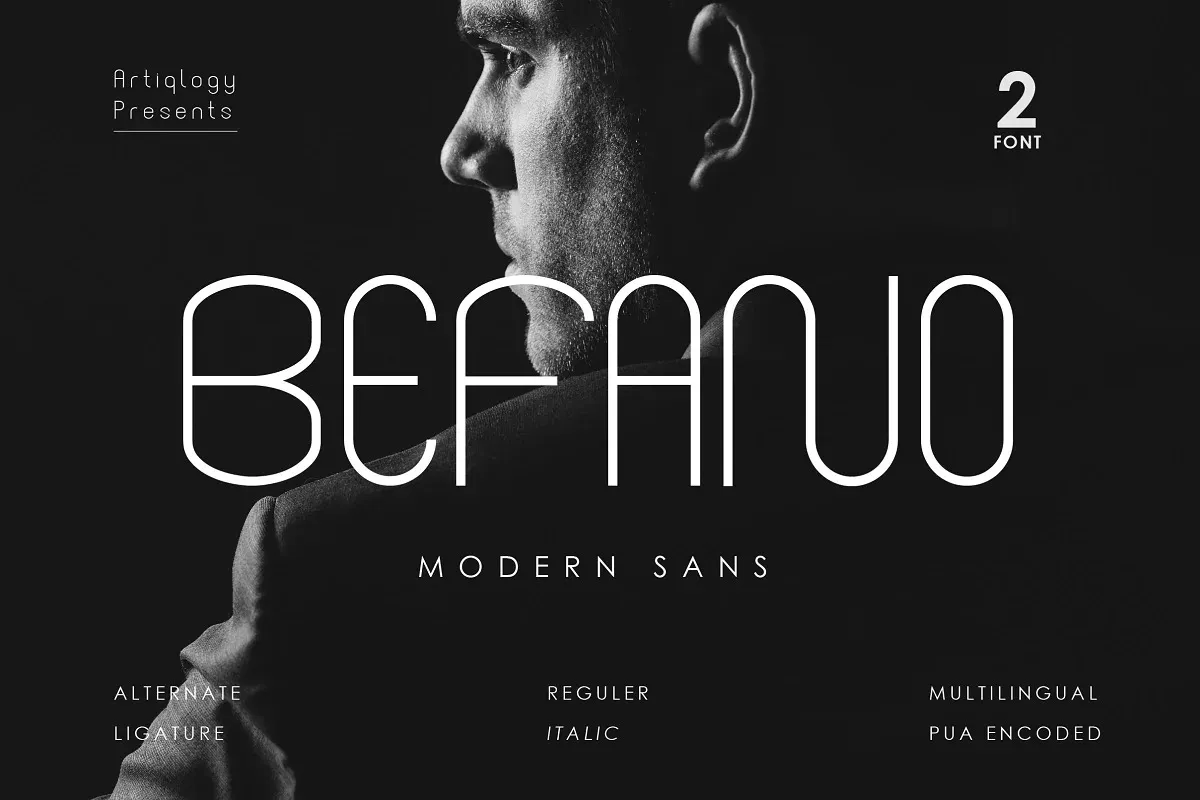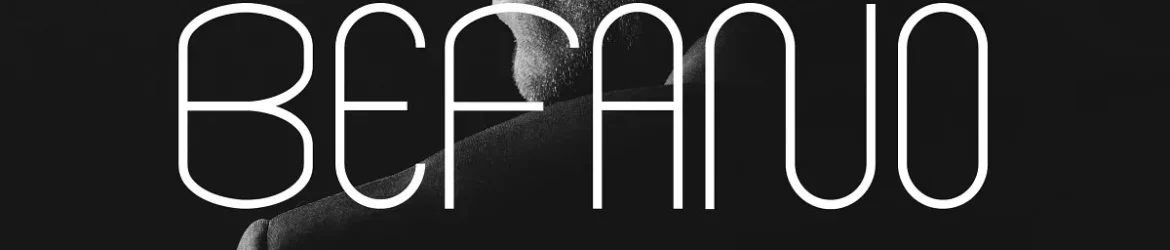
A fonte BEFANO Font é uma escolha perfeita para projetos que exigem uma aparência moderna e minimalista. Desenvolvida pelo designer de fontes Artiqlogy, ela traz a simplicidade pura do tipo sérvico acompanhada por um toque arredondado de delicadeza. Suas formas leves e suas linhas clean são perfeitas para criar projetos criativos, como logotipos de marcas, rótulos de camisetas, banners e até mesmo design escolar, dando vida a uma ampla gama de ideias e estilos. Com seu estilo suave e versátil, BEFANO é uma fonte sérvica ideal para qualquer situação onde você precisa de um olhar fresco e moderno.